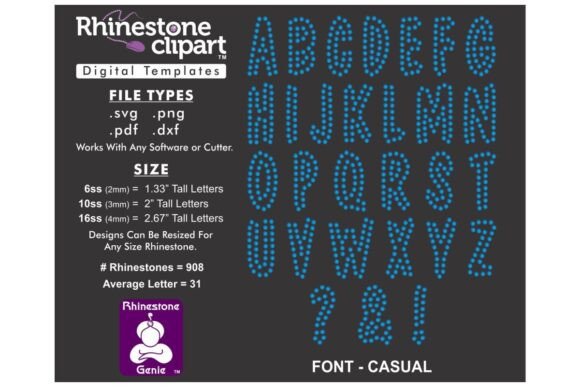
Rhinestone Design FONT - CASUAL 2"
قد يكون العثور على عناصر التصميم المناسبة أمرًا صعبًا، ولكن Rhinestone Design FONT - CASUAL 2" يقدم مجموعة استثنائية ترتقي بعملك على الفور.
تم تصميمه بدقة، ويوفر Rhinestone Design FONT - CASUAL 2" متجهات نظيفة وطباعة سلسة وترخيصًا تجاريًا لراحة بالك.
سواء كنت تقوم بإنشاء منتجات الطباعة عند الطلب أو دعوات الزفاف أو رسومات وسائل التواصل الاجتماعي، فإن Rhinestone Design FONT - CASUAL 2" هو الخيار المثالي.